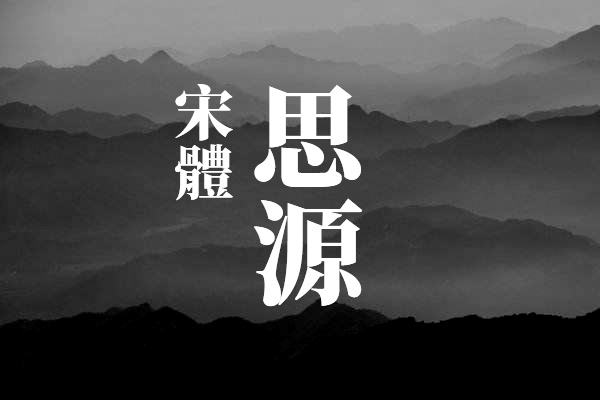
思源宋体-繁体中文版
谷歌与Adobe携手发布了一款全新的开源字体——思源宋体(Source Han Serif),这款字体支持四种不同的东亚语言,包括简体中文、繁体中文、日文和韩文。此外,它还提供了七种字体粗细形式的共65,535个字形(OpenType格式支持的最大上限),以确保视觉审美的一致性,并满足各种不同的排版需求。
在视觉上,可能会有一些人认为这四种语言的字形是相同的中文字体,但实际上,思源宋体为每种语言都设计了多达四个区域差异化的字形设计,确保了字体在不同地区和文化背景下的适用性和辨识度。
思源宋体的设计涵盖了所有这些字形变体,并为这些区域化字形进行了精心设计。通过支持多种语言和字体粗细形式,思源宋体为全球范围内的读者提供了更加丰富、个性化的阅读体验。
思源宋体-繁体中文版效果预览